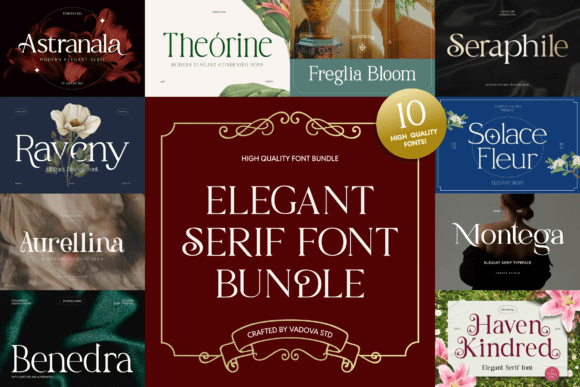
Elegant Serif Bundle
قد يكون العثور على عناصر التصميم المناسبة أمرًا صعبًا، ولكن Elegant Serif Bundle يقدم مجموعة استثنائية ترتقي بعملك على الفور.
سواء كنت تقوم بإنشاء منتجات الطباعة عند الطلب أو دعوات الزفاف أو رسومات وسائل التواصل الاجتماعي، فإن Elegant Serif Bundle هو الخيار المثالي.